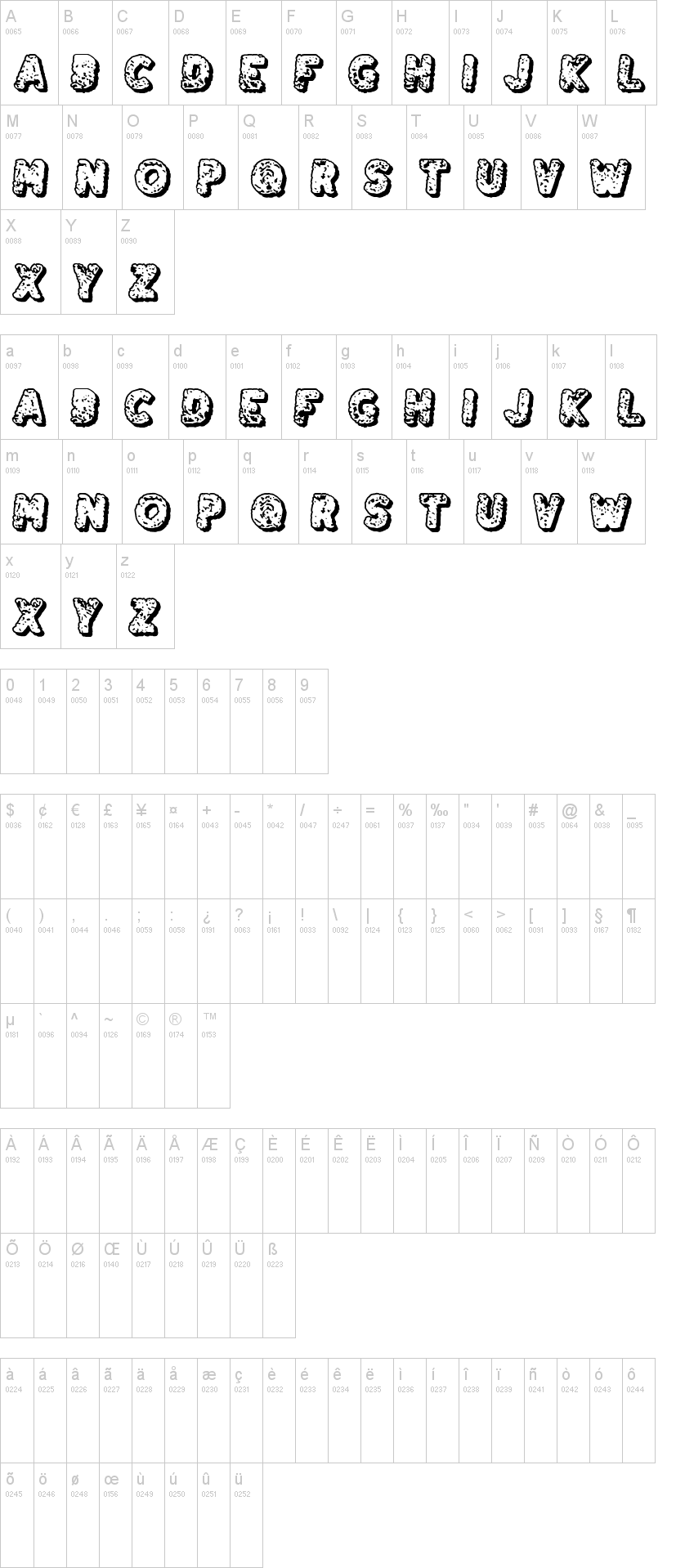
Destroy the Enemy
Destroy the Enemy 是一款十分特殊的字体,它的设计灵感来源于军事文化,并且具有粗犷、强烈的外观。它的字体特点是拥有复古的线条,以及一些独特的符号,如炮口、枪支等。这种字体适合用于军事或枪支相关的行业,也可用于游戏、电影等其他行业。它的特点是有力、有力量,能够传达出强烈的感受。
Destroy the Enemy是一款非常不错的手写艺术字体,具有很好的视觉感,适合于文化类的宣传设计、商业类品牌的广告和产品包装设计以及个性化文字排版等较多场景。
Destroy the Enemy字符映射图